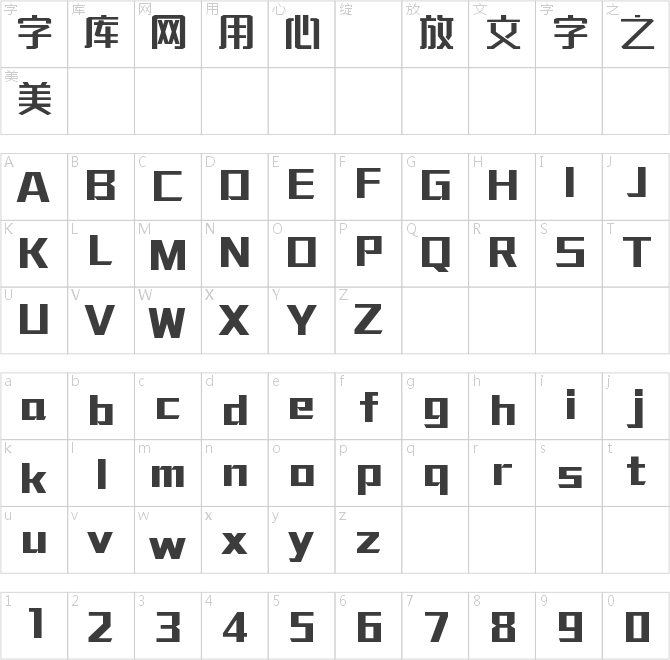
字体名称: 素材集市酷方体
2020年4月初,素材集市招募十二名各行业现役设计师,组建了字集团队,“素材集市酷方体”是字集团队的首款原创字库。经过几个月的艰苦奋战,“素材集市酷方体”已完成了汉字+字符2628个,能基本满足一般的设计需求。素材集市酷方体于2020年8月10日(星期一)正式发布!并且是免费商用!免费商用!免费商用!
素材集市酷方体字体字库是一款让人赏心悦目、百看不厌的中文字体,适合各类广告和产品包装设计应用,字体大小0.45MB,格式为ttf字体,上传用户是迷路的猪,作者/版权方为素材集市